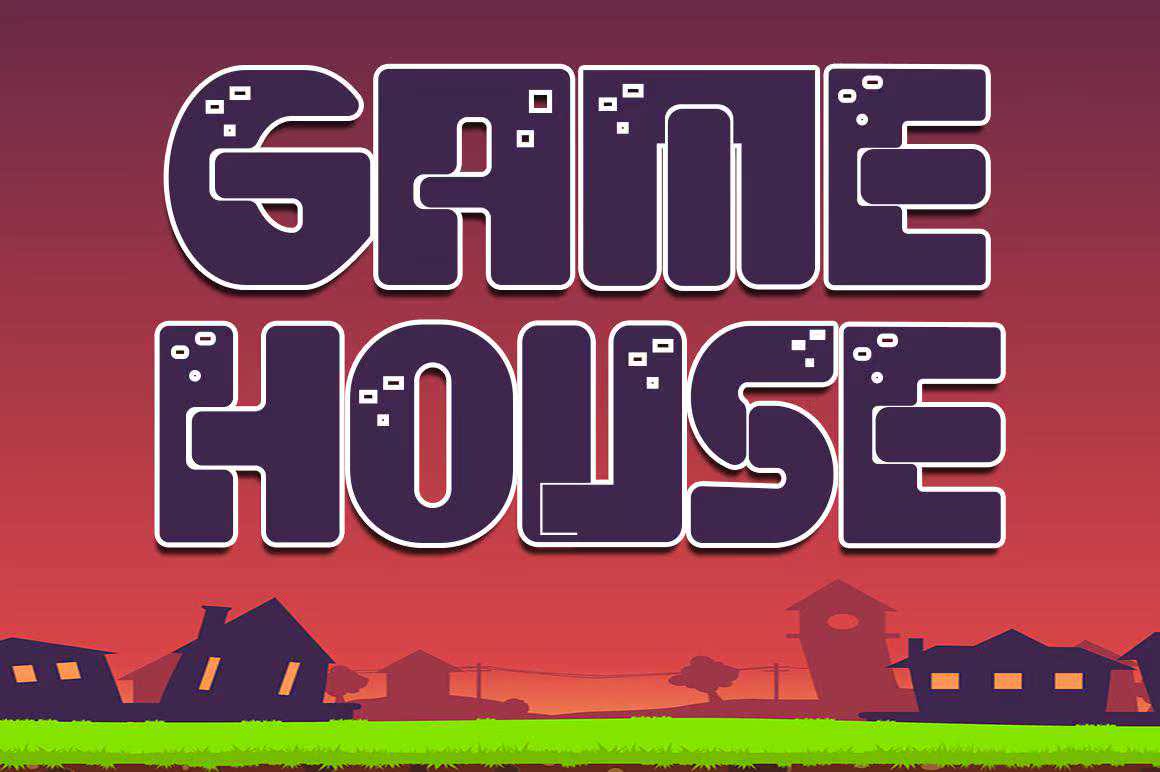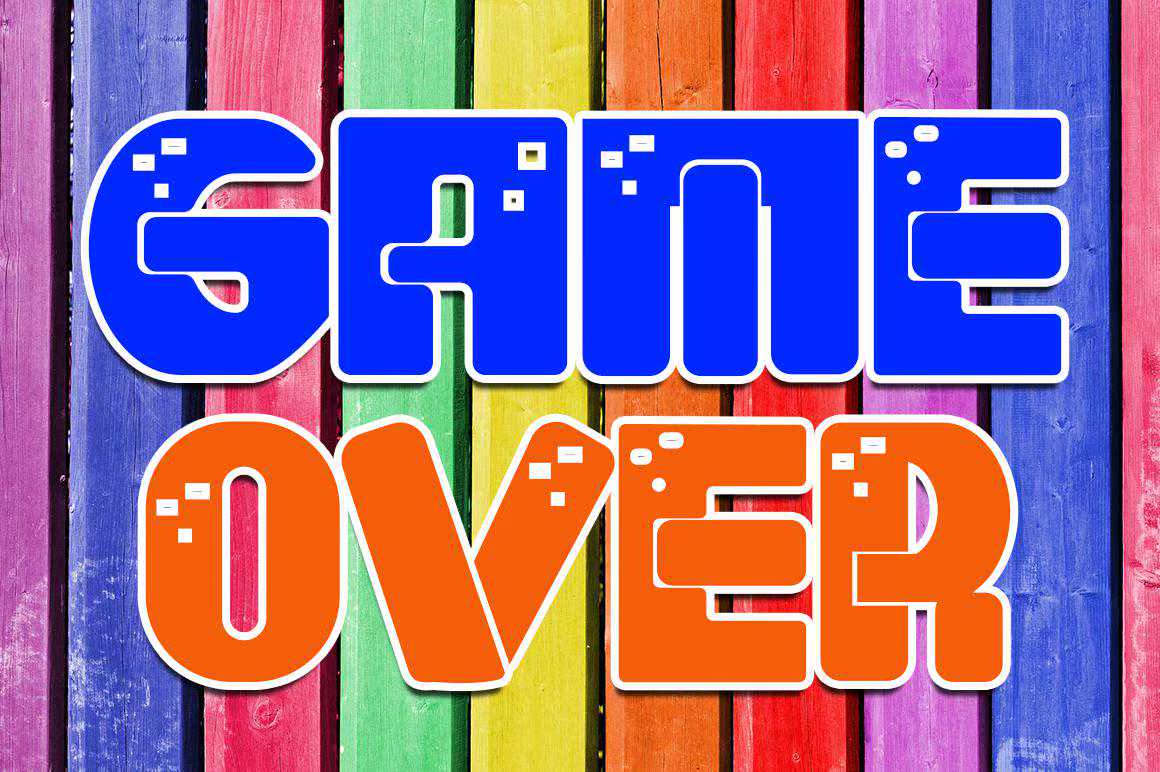
Game SharkisAcool和CartonLikedDisplayFont.ItemBody可显示性和验证性,并可区分所有儿童活动或学校项目的完美选项。将此ChunkyletteredFont添加到您的设计中,并注意它如何使MCome激活!Game SharkisAcool和CartonLikedDisplayFont.ItemBody可显示性和验证性,并可区分所有儿童活动或学校项目的完美选项。将此ChunkyletteredFont添加到您的设计中,并注意它如何使MCome激活!